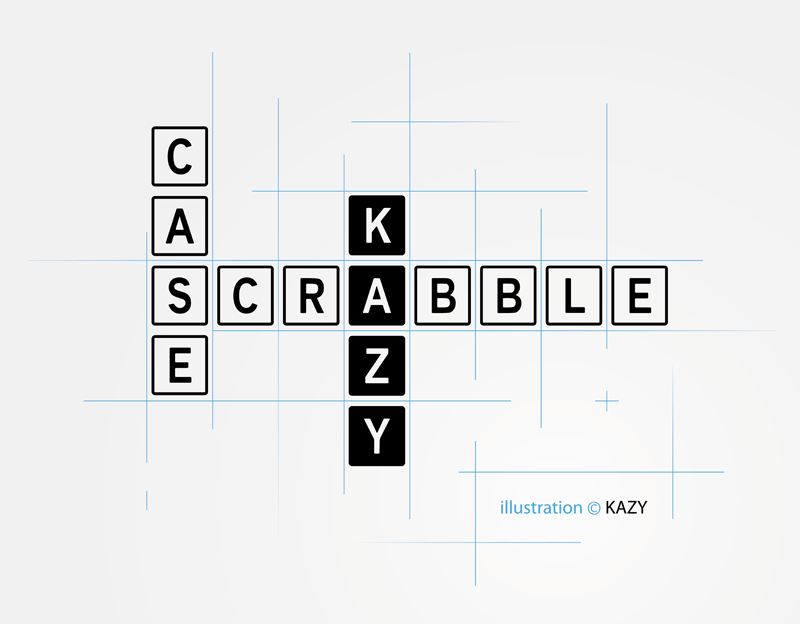
Font name: | KazyCase Scrabble |
Author: | Emmanuel Didier |
Note by Emmanuel Didier | |
��KAZYcase scrabble�� est une police d�co gratuite, utilisable dans quelques pays d�Europe. Vous pouvez alterner les carr�s blancs et noirs pour vos compositions. Les Majuscules sont noires et les minuscules blanches. J�appr�cie avec plaisir vos dons Compte paypal pour les dons : flashpict@gmail.com Merci pour votre soutien. Bien � vous. Kazy _______________________________ "KAZYcase scrabble" is a free decorative font that can be used in some countries in Europe. You can alternate the white and black squares for your compositions. Upper case letters are black and lower case letters white. I appreciate your donations with pleasure Paypal account for donations: flashpict@gmail.com Thank you for your support. Yours truly. Kazy |